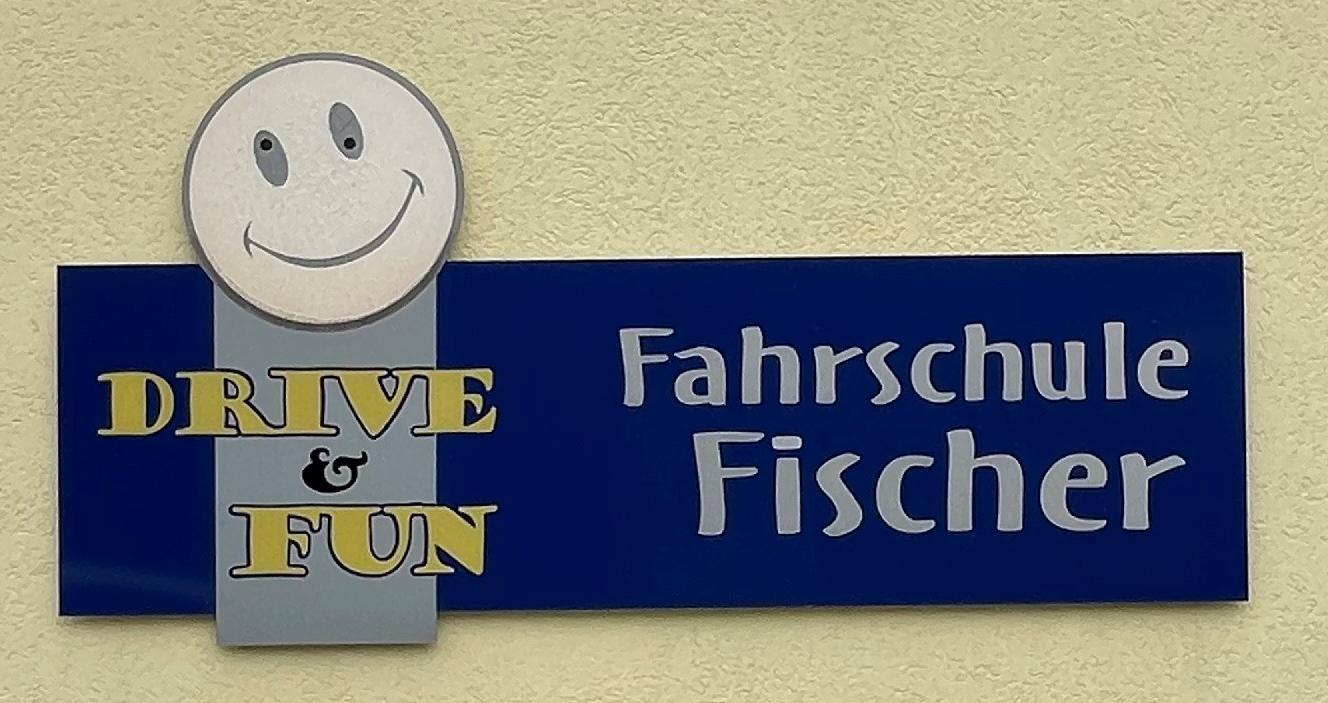
Schrift von "Fahrschule Fischer" Ende 90er
Ich suche die Schrift von dem angehängten "wunderschönen" Logo der Fahrschule Fischer. Es geht um den rechten Teil.
Schätzungsweise wurde das Logo in den 90er erstellt, leider habe ich keine näheren Infos.
Es ist wohl tatsächlich eine um 120 % »geweitete« Oz Handicraft, habe gerade mal einen Test gemacht, denn mir kam sie auch so bekannt vor … (… aus der Zeit, wo es neben FF Kosmik, FF Justleftahnd etc. eben nicht viel gab.)